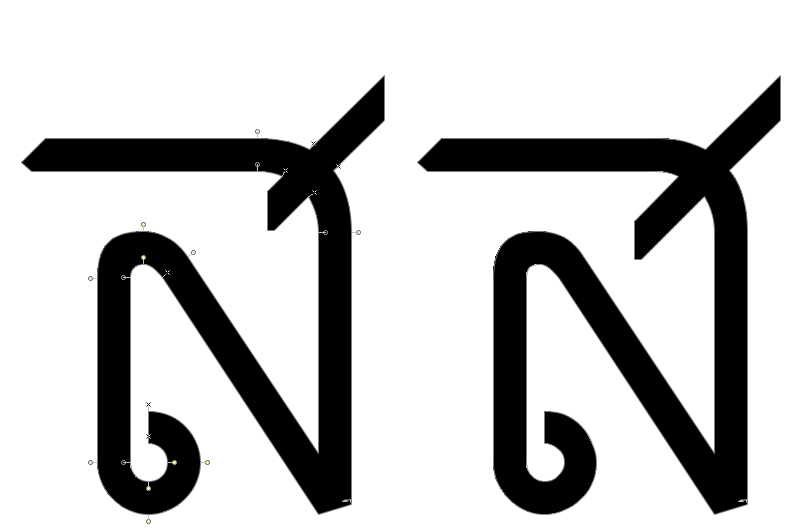
ฝากตรวจการบ้าน ฟอนต์ ครับ
ลองปรับแก้ตามคำแนะนำแล้ว เอารูปมาให้ดูสิ่งที่ปรับเปลี่ยนครับ
ด้านซ้ายมือ เป็นตัวปรับแก้นะครับ
ขอไข่
ฃอฃวด
ฆอระฆัง
ชอช้าง
ซอโซ่
ยอยักษ์
และสอเสือ
ส่วน ว ปรับให้ส่วนบนให้สั้นลงนิดนึง แก้ให้สมดุลขึ้นครับ แต่ไม่ได้อัพรูปครับ
อยากเห็นฉบับปรับปรุงเป็นข้อความจังค่ะ
ต้องสวยมากแน่เลย :25:
ลองใส่ในข้อความครับ
คิดว่าคงจะปล่อยแล้วอ่ะครับ  ให้ลองใช้กัน แล้วค่อยปรับปรุงกันต่อไปครับ
แอบรู้สึกว่า ผ ผึ้ง มันสอบแหลมโดดจากชาวบ้านไปนิดแฮะ
เวลาพิมพ์เป็นข้อความ มองแล้วสะดุดเลยล่ะ
ยิ่งพอย้อนกลับไปเทียบกับ พ พาน แล้ว อืมมมม มันสวยนะ แต่แค่มันโดดน่ะ
หรือทำเพื่อให้มันต่างกันมากๆ ก็แล้วแต่เจตนาจ้ะ  :22:
ผมว่าตอนนี้มันเป็นเรื่องดีเทลเล็กๆ น้อยๆ ครับ ต้องค่อยๆ ดู อย่างเช่น ไม้หันอากาศกับไม้โท มันตีกันเกินไปมั้ย ฯลฯ
อ้อ แล้วก็เรื่องความแคบ - กว้าง ของแต่ละตัวครับ
ตย. เช่น ผ ผึ้ง เห็นไหมครับว่าพอมันอยู่กับ ย ยักษ์ มันกลายเป็นดูแคบมาก ทั้งๆ ที่ตามหลักแล้วมันควรจะกว้างกว่า
ใช่ครับ คือตั้งใจนิดนึง เพราะรู้สึกว่าถ้ามันตรงเหมือน พ พาน มันจะเหลี่ยมตรงกันเกินไป เป็นการแก้เลี่ยน (ความรู้สึกส่วนตัวจริงๆครับในส่วนนี้)
เดี๋ยวปรับ ไม้โทขึ้นเพื่อไม่ให้ตีกันเกินไปครับ แล้วก็ยืด ผ ผึ้ง ให้กว้างอีกนิดนึง ส่วนตัวอื่นค่อยๆดูไปครับ
เย้ ใกล้ได้ปล่อยแล้ว :30:
ปรับแก้ตัว ผ ผึ้ง ฝ ฝา กับเรื่อง วรรณยุกต์ และอะไรอีกยิบย่อย
พอมาลองพิมพ์แบบนี้แล้วแย่เลยครับ :08:
หลงใหล๋ มันสะกดยังงี้ได้ยังไง ต้องหลงใล๋สิ
ขอโทษจริงๆครับ  :05: ผมไม่ได้ตั้งใจให้สะกดผิด แค่ต้องการลองดู ตัว จักวา กับต้วไม้ ใ